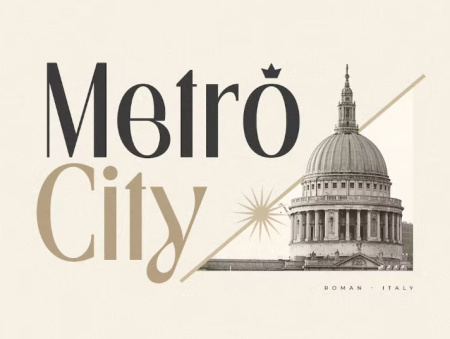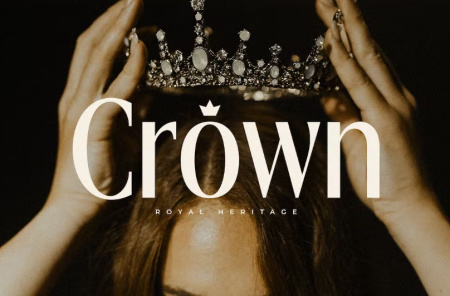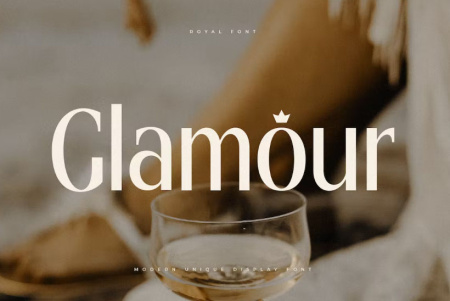
فونت انگلیسی لوکس و فانتزی Royal
یک فونت لوکس فانتزی، منحصر به فرد و همه کاره است، فونتی که می توانید آن را با هم ترکیب کنید تا هر گونه تنوع و شکل منحصر به فرد را به راحتی تنها در چند ثانیه با انتخاب جایگزین از آنها به دست آورید. این فونت انگلیسی لوکس و فانتزی Royal با کنتراست متوسط است که برای پروژه های برندسازی، لوگو، طرح های عروسی، پست های رسانه های اجتماعی، تبلیغات، بسته بندی محصولات، طرح های محصول، برچسب، عکاسی، واترمارک، دعوت نامه، لوازم التحریر و هر پروژه ای مناسب است. برای دریافت این فونت با لینک مستقیم از gfxdownload.ir به ادامه مطلب مراجعه کنید.